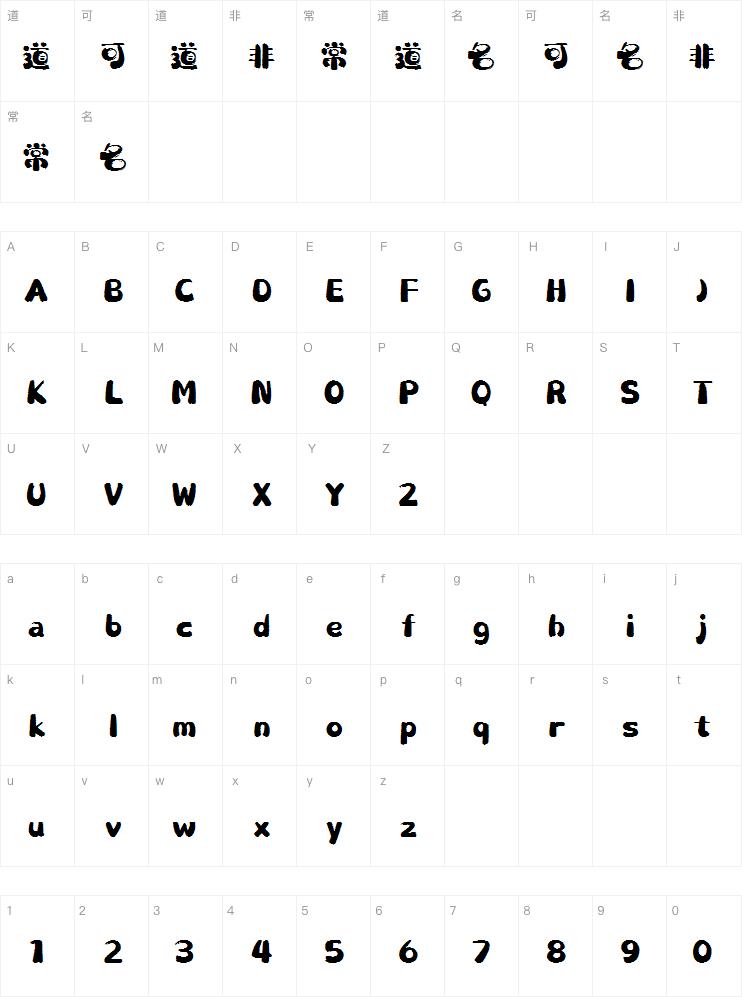
上首流光体
上首流光
上首流光体,简体中文约6763字。这套字体在字形设计上,融合古朴与灵动,笔画如流转光影,既有圆润舒展的形态,又暗含遒劲张力,似时光在笔墨间缓缓淌过。在笔画细节处理上,刻意营造出富有韵律的粗细变化与边缘质感,让每一个字都仿若承载着岁月的流光,于静态中传递出动态的视觉韵律,为文字赋予独特的艺术表现力与视觉吸引力。
上首流光体